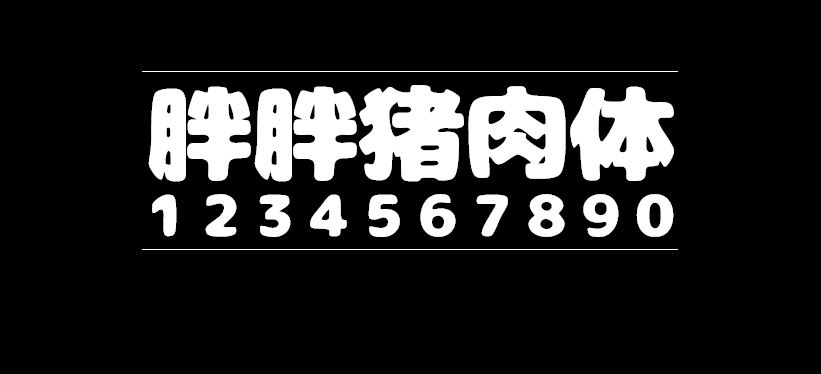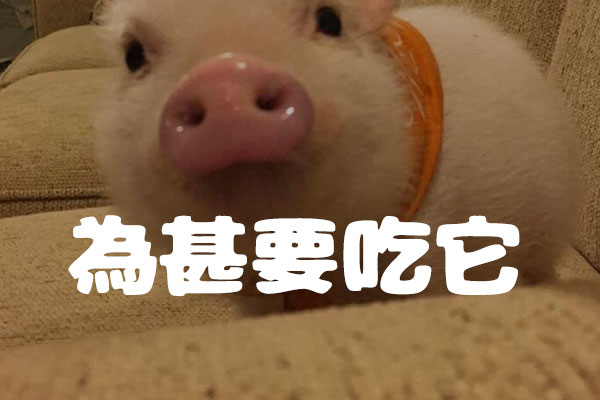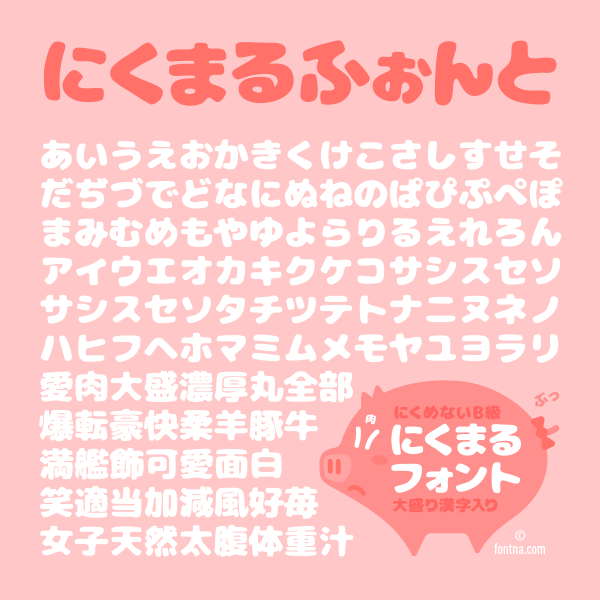
胖胖猪肉体
胖胖猪肉体 (日文名: にくまるフォント 英文名:07 NikumaruFont) 是一款胖乎乎圆滚滚的可爱日系字体,以松散、软糯、柔和的气氛为特征的字体。虽然与美丽、正确无缘,但却给设计增添了外行般的乐趣。它是基于M+ FONTS进行改造制作而成的字体。 字体包含日本JIS第1水准2965字,第2水准3390字。简体字符相对较少,繁体字符比较多。 由于这款字体是基于M+ FONTS改造的字体,而M+ FONTS是日本一款免费开源的字体,所以胖胖猪肉体可以免费使用于任何场景,包括商用。无论是商用还是非商用都可以使用,请放心下载。.